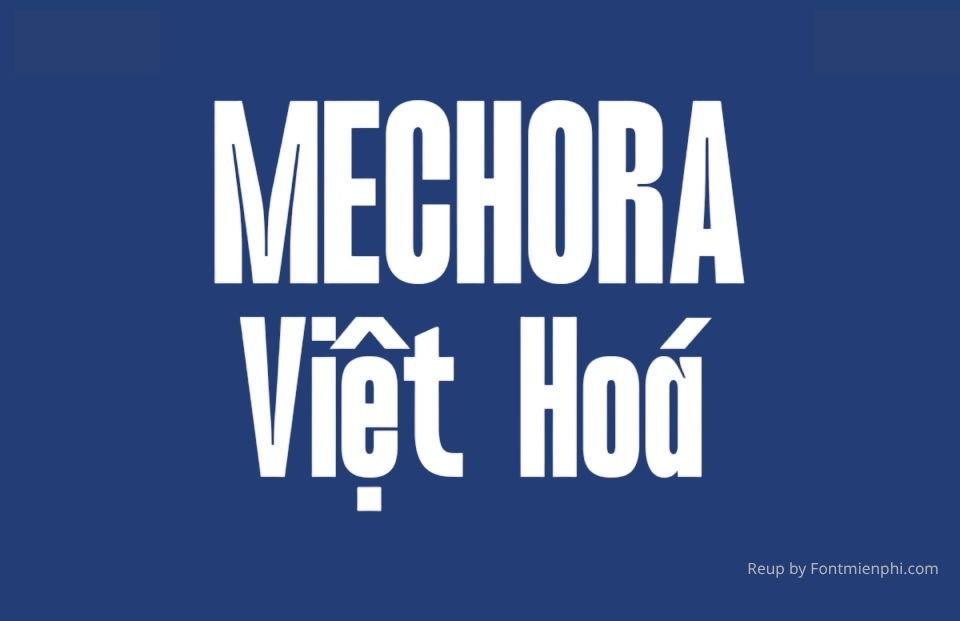
Font Việt hóa 1FTV VIP Mechora
Việc Việt hóa đặc biệt hữu ích với designer thường xuyên thực hiện ấn phẩm cho thị trường trong nước. Khi kết hợp cùng bộ gõ tiếng Việt và thiết lập bảng mã phù hợp, người dùng có thể nhập nội dung nhanh chóng trong các phần mềm thiết kế quen thuộc. Đây là lợi thế rõ rệt so với phiên bản font quốc tế chưa được bổ sung ký tự tiếng Việt, vốn có thể làm mất dấu hoặc khiến một số chữ hiển thị không đồng đều.
• Hỗ trợ các ký tự và dấu phổ biến trong tiếng Việt.
• Giúp nội dung tiêu đề hiển thị đồng bộ về phong cách.
• Giảm thời gian xử lý lỗi chữ hoặc thay thế ký tự thủ công.
• Thuận tiện khi thiết kế ấn phẩm truyền thông cho người dùng Việt Nam.
Phong cách cơ khí, công nghệ và tương lai nổi bật
1FTV VIP Mechora sở hữu cá tính thị giác phù hợp với các chủ đề liên quan đến công nghệ, máy móc, robot, thể thao điện tử, trò chơi, ô tô, tốc độ hoặc khoa học viễn tưởng. Hình dáng chữ tạo cảm giác cứng cáp và có cấu trúc, nhờ đó dễ thu hút sự chú ý khi được đặt ở vị trí trung tâm của bố cục.
Font đặc biệt phù hợp với những dự án muốn truyền tải tinh thần đổi mới, sức mạnh và sự hiện đại. Khi sử dụng ở kích thước lớn, các đặc điểm tạo hình của chữ được thể hiện rõ ràng hơn, giúp tiêu đề trở thành một yếu tố đồ họa độc lập. Người thiết kế cũng có thể kết hợp font với hiệu ứng kim loại, ánh sáng, đường viền, đổ bóng hoặc các bề mặt vật liệu để tăng chiều sâu cho sản phẩm.
Để đạt hiệu quả tốt, nên dùng Mechora cho tiêu đề chính, tiêu đề phụ ngắn hoặc nội dung cần nhấn mạnh. Với đoạn văn dài, người dùng có thể phối hợp cùng một font chữ đơn giản và dễ đọc hơn. Cách kết hợp này vừa giữ được cá tính của thiết kế, vừa bảo đảm người xem tiếp nhận thông tin thuận lợi.
Ứng dụng linh hoạt trong nhiều sản phẩm thiết kế
Font Việt hóa 1FTV VIP Mechora có thể được ứng dụng trong nhiều loại ấn phẩm số và ấn phẩm in. Từ banner mạng xã hội, ảnh bìa, thumbnail video đến poster sự kiện hoặc bao bì sản phẩm, font đều có khả năng tạo ra điểm nhấn rõ ràng nếu được sử dụng đúng ngữ cảnh. Phong cách độc đáo của Mechora cũng giúp thương hiệu xây dựng diện mạo khác biệt so với các thiết kế dùng kiểu chữ quá quen thuộc.
Một số gợi ý ứng dụng nổi bật gồm:
1. Thiết kế logo hoặc biểu trưng chữ cho thương hiệu công nghệ, gaming và phụ kiện máy tính.
2. Tạo tiêu đề poster phim, trò chơi, sự kiện thể thao điện tử hoặc chương trình giải trí.
3. Thiết kế banner quảng cáo, ảnh bìa fanpage, bài đăng mạng xã hội và thumbnail video.
4. Trang trí áo thun, sticker, bao bì, nhãn sản phẩm và các vật phẩm cá nhân hóa.
5. Xây dựng tiêu đề cho website, landing page hoặc nội dung giới thiệu sản phẩm mới.
Tùy theo mục tiêu truyền thông, người dùng có thể điều chỉnh kích thước, khoảng cách chữ, màu sắc và hiệu ứng để tạo nhiều sắc thái khác nhau. Tông màu bạc, đen, xám hoặc xanh lạnh thường làm nổi bật chất cơ khí; trong khi đỏ, cam hoặc vàng có thể mang đến cảm giác tốc độ và năng lượng. Tuy nhiên, nên tiết chế số lượng hiệu ứng để giữ cho chữ rõ ràng và tránh làm bố cục trở nên nặng nề.
Dễ phối hợp với bố cục và các font chữ bổ trợ
Mặc dù mang phong cách mạnh, Font Việt hóa 1FTV VIP Mechora vẫn có thể kết hợp linh hoạt với nhiều hệ thống thiết kế nếu người dùng phân cấp nội dung hợp lý. Font nên đảm nhiệm vai trò thu hút sự chú ý, trong khi các đoạn mô tả, thông tin chi tiết hoặc chú thích nên sử dụng một kiểu chữ trung tính. Sự tương phản giữa font trang trí và font nội dung sẽ giúp bố cục vừa có điểm nhấn, vừa duy trì trải nghiệm đọc tốt.
Khi thiết kế logo hoặc tiêu đề, bạn có thể tăng nhẹ khoảng cách giữa các ký tự để tạo cảm giác rộng rãi và hiện đại. Đối với poster hoặc banner, việc căn chỉnh chữ theo lưới sẽ giúp hình khối của Mechora hòa hợp hơn với hình ảnh, biểu tượng và các yếu tố đồ họa khác. Nếu đặt chữ trên nền phức tạp, nên bổ sung lớp màu, đường viền hoặc vùng tương phản để nội dung không bị chìm.
• Ưu tiên kích thước lớn để thể hiện rõ đặc trưng của font.
• Không nên dùng toàn bộ font cho những đoạn văn quá dài.
• Kiểm tra dấu tiếng Việt sau khi nhập nội dung trong phần mềm.
• Giữ khoảng cách dòng và khoảng cách chữ phù hợp với từng bố cục.
• Kết hợp màu sắc có độ tương phản tốt để tăng khả năng nhận diện.
Hỗ trợ gõ tiếng Việt đầy đủ và thuận tiện
Chức năng quan trọng nhất của Font Việt hóa 1FTV VIP Mechora là hỗ trợ soạn thảo nội dung tiếng Việt có dấu. Font có thể được sử dụng cho các câu tiêu đề, khẩu hiệu, tên sản phẩm, tên thương hiệu hoặc thông điệp quảng cáo bằng tiếng Việt,chọn Mechđại, phù hợp với những thiết kế cần tạo cảm giác mạnh mẽ, sắc nét và giàu cá tính. Phiên bản Việt hóa hỗ trợ đầy đủ dấu tiếng Việt, giúp nhà thiết kế, người sáng tạo nội dung và chủ